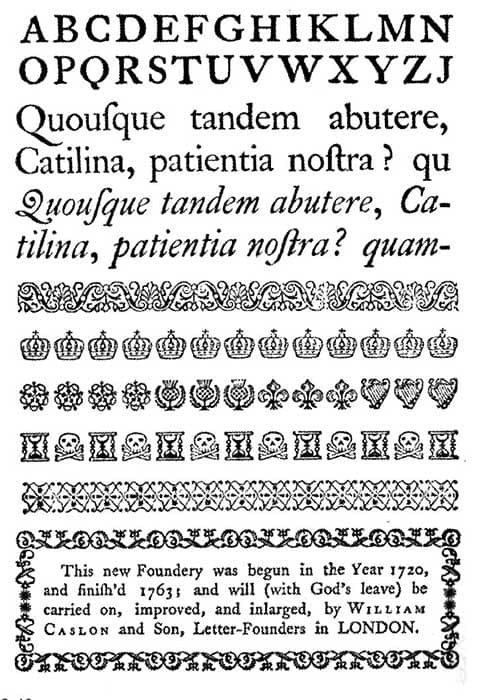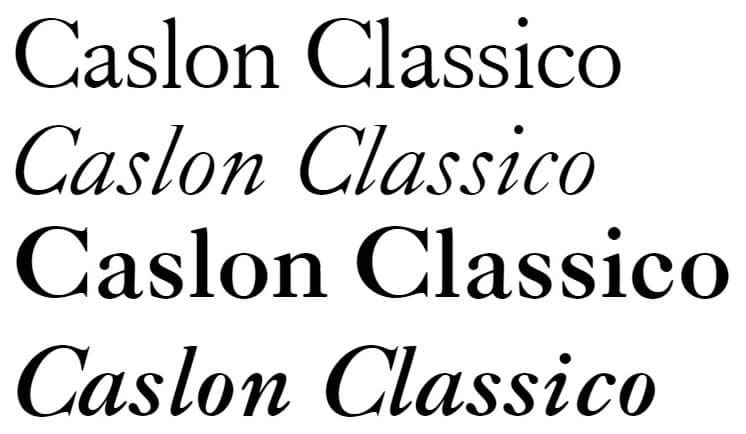
Caslon es una familia tipográfica de origen europeo, de gran legibilidad y elegancia, creada en 1725 en Londres.
La familia tipografía CASLON tiene su primer versión en el año 1725 por William Caslon (nace en 1692, Cradley, Worcestershire, Inglaterra, muere el 23 de enero del año 1766 en Bethnal Green, Londres), Caslon se inspira en los diseñadores Holandeses: Christoffel van Dijcks y Dirck Voskens
Es una de las primeras tipografías creadas por William en su taller independiente en Londres, donde durante más de 60 años diseña y funde fuentes tipográficas.
El tipo Caslon entra dentro de las serif (terminaciones decorativas o adornos, patas ), su mancha tipográfica aporta una excelente legibilidad y lectura. Este tipos es popular en su época dentro de Inglaterra, es utilizada por la Casa Real para la impresión de todos sus documentos. En Estados Unidos es usada para redactar la declaración y constitución Estados Unidos.
Caslon en la actualidad
En la actualidad existen varios font, con reminiscencias Caslon:
- Justin Howes en 1998 realiza la versión para ITC estudiandia e investiga la font / fuente original.
- Adobe tiene revival realzada por diseñadora Carol Twombly.
- Franko Luin 1993 llamada Caslon Classic,